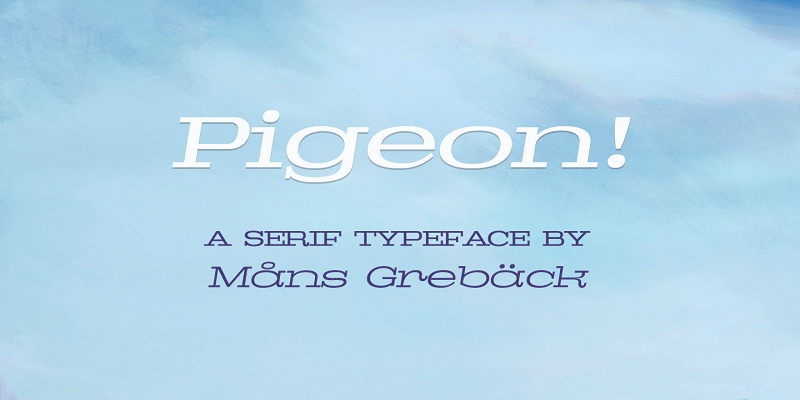
A Pigeon Font Family é uma elegante escolha para designers que buscam achar um equilíbrio entre modernidade e sofisticação. Esta slab serif fonte foi criada por Måns Grebäck, designer de gráficos respeitado, fornecendo linhas finas e levemente estilizadas que se adaptam bem em textos tanto legíveis quanto atraentes. Ideal para ambientes como websites corporativos, editoriais e materiais de marketing impressos, a Pigeon oferece uma personalidade única que complementa bem o seu estilo de trabalho. Para usufruir desta fonte em sua produção comercial, visite www.mansgreback.com/fonts/pigeon.
Designer: Måns Grebäck